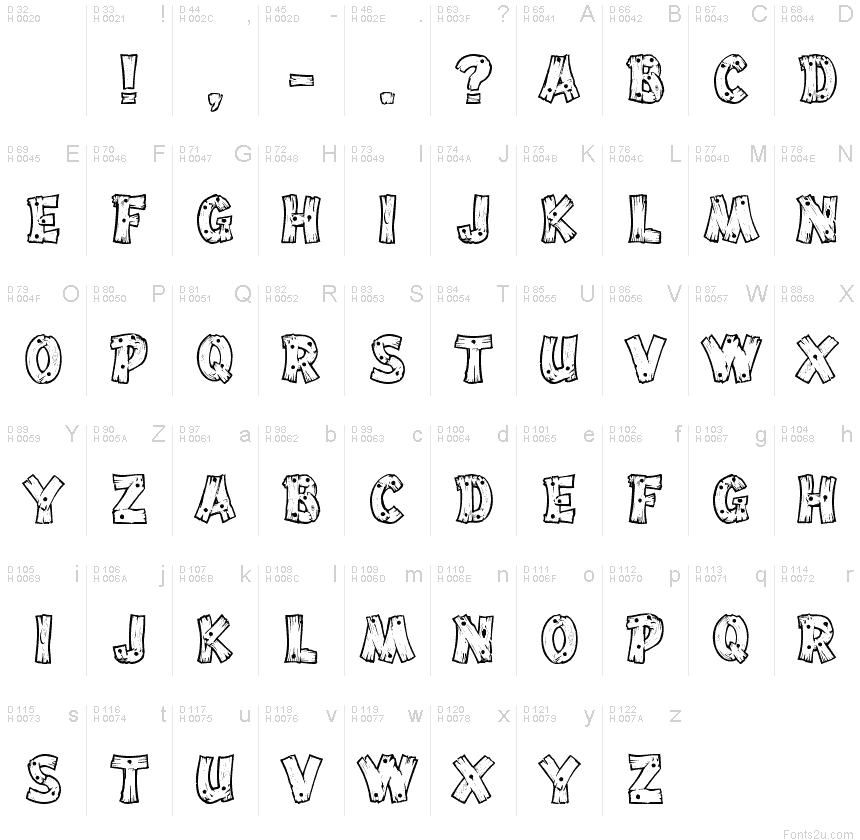
DriftType je bezplatné dekorativní písmo, které vypadá jako vyřezané ze surových dřevěných prken. Každé písmeno nese organické letokruhy, suky a lehce roztřepené okraje, což dodává vašim slovům hmatatelný, ručně opracovaný pocit, který je hravý a zároveň drsný. Pevné, vertikální proporce udržují texturu pod kontrolou, takže zůstává dobře čitelné i ve větších velikostech.
Použití DriftType ve vašich projektech přináší okamžitou energii dobrodružství a pohádkového světa. Skvěle se hodí na obálky dětských knih, dobrodružné plakáty, letáky na tábory, pozvánky na pirátské večírky, herní loga a grafiku pro sezónní akce. Toto bezplatné písmo vynikne, když ho nastavíte na velkou velikost a zkombinujete s jednoduchým, neutrálním bezpatkovým písmem pro doprovodný text, čímž necháte písmena ve stylu dřevořezu, aby vytvořila všechen ten charakter a působivý dojem.